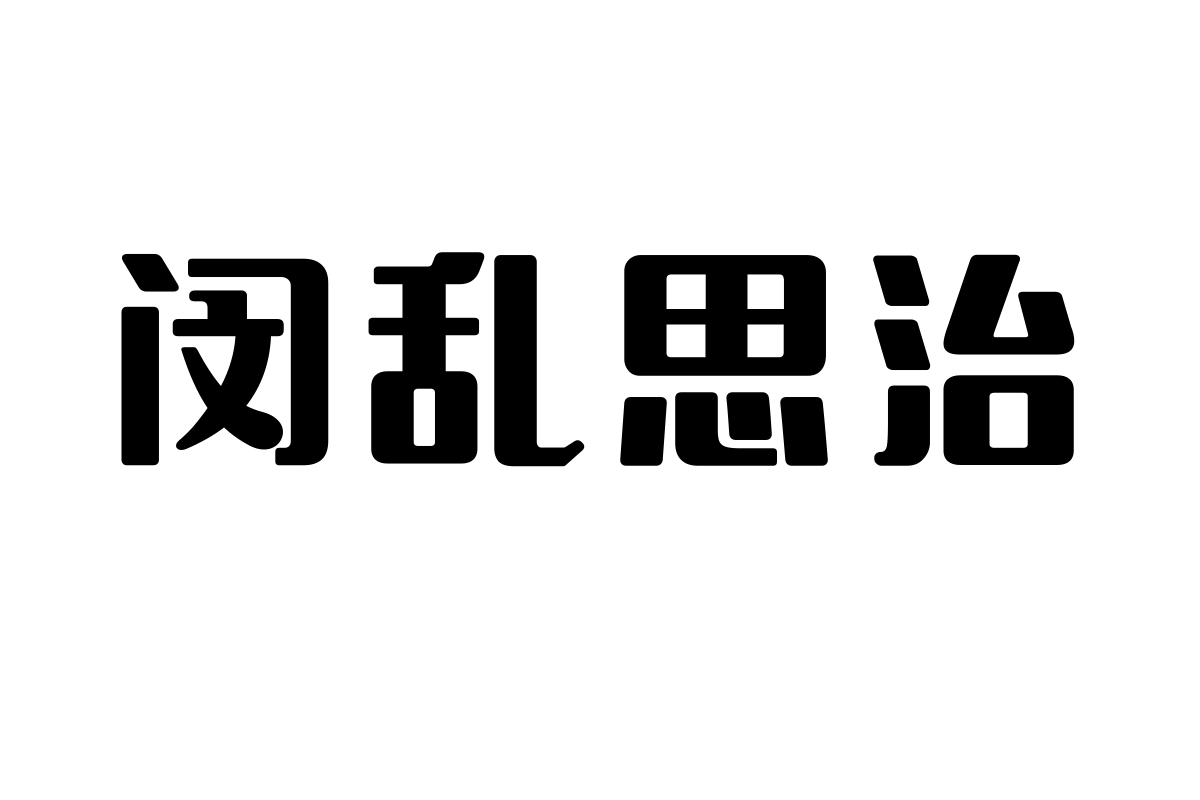
文道艺术黑是一款现代、简洁的无衬线字体,具有很高的辨识度和可读性。这款字体的特点是字形结构规整,笔画流畅,适合用于标题、正文、广告等场合。其特点是:
1. 字形规整:文道艺术黑的字形结构规整,笔画清晰,易于阅读和识别。
2. 可读性强:该字体具有较高的可读性,适用于各种文字内容,包括标题、正文、广告等。
3. 应用场景广泛:文道艺术黑适用于各种场景,如书籍、杂志、报纸、网站、广告等。
4. 风格简约:文道艺术黑的设计简约,没有过多的装饰元素,给人一种干净、清爽的感觉。